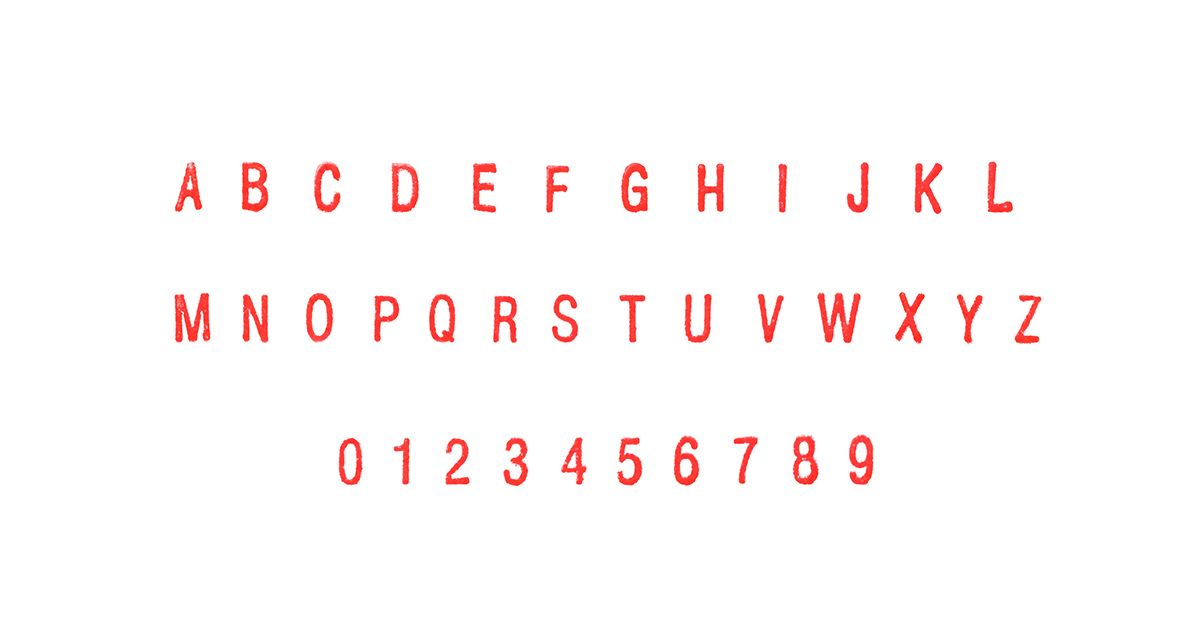
Descarga gratis: Plantilla con tipografías del abecedario para crear tu sello personal
Descarga gratis plantillas de tipografías del abecedario ideales para el tallado a mano. Son perfectas para practicar o para crear tu set de sellos único.
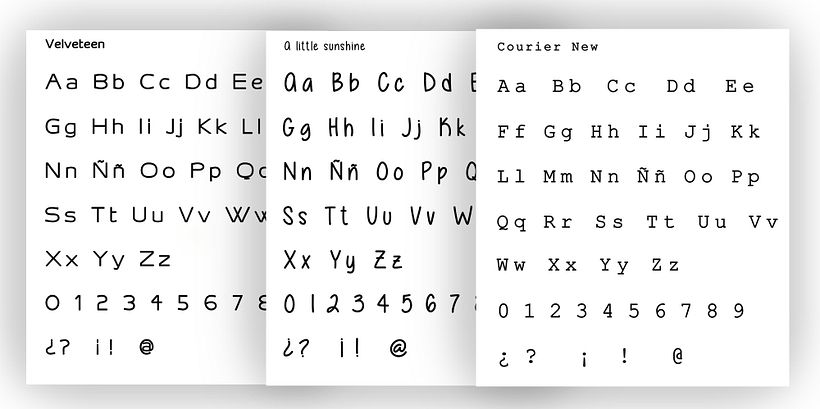
Una forma más de expresar tu propia identidad es a través de los ex libris. Estos pequeños sellos decorativos y artísticos sirven para expresar tu identidad y estilo de una forma única y muy personal. Los ex libris tienen su origen en la antigüedad y, a través de los siglos, su función ha sido la de marcar la propiedad de los libros de una biblioteca. Su diseño representaba la identidad de su propietario, daba información sobre quién era o sobre su profesión.
El proceso para crear un ex libris es tan interesante como su función. Para diseñar un ex libris se usa la técnica del tallado a mano con la que puedes experimentar tanto con imágenes como con tipografía. María López (@marialopezprint) es artista y grabadora y está especializada en sellos personalizados. Con el grabado de sellos realiza retratos, logos, motivos decorativos y tipografías para clientes que buscan comunicar su identidad de una forma original. Su técnica de tallado es sobre goma, con la que ha aprendido el valor de la paciencia, que, sin duda, le trae grandes recompensas.
Esta artista comparte contigo en esta descarga diferentes plantillas con las que podrás crear diferentes tipografías en la creación de tu sello personal. En este documento, que puedes descargar gratis, vas a encontrar diferentes tipografías adecuadas para el tallado a mano. Descárgatelas y practica mucho antes de empezar a tallar. Elige las que más se adaptan a tu estilo y empieza a crear tu propio set de sellos de abecedario.